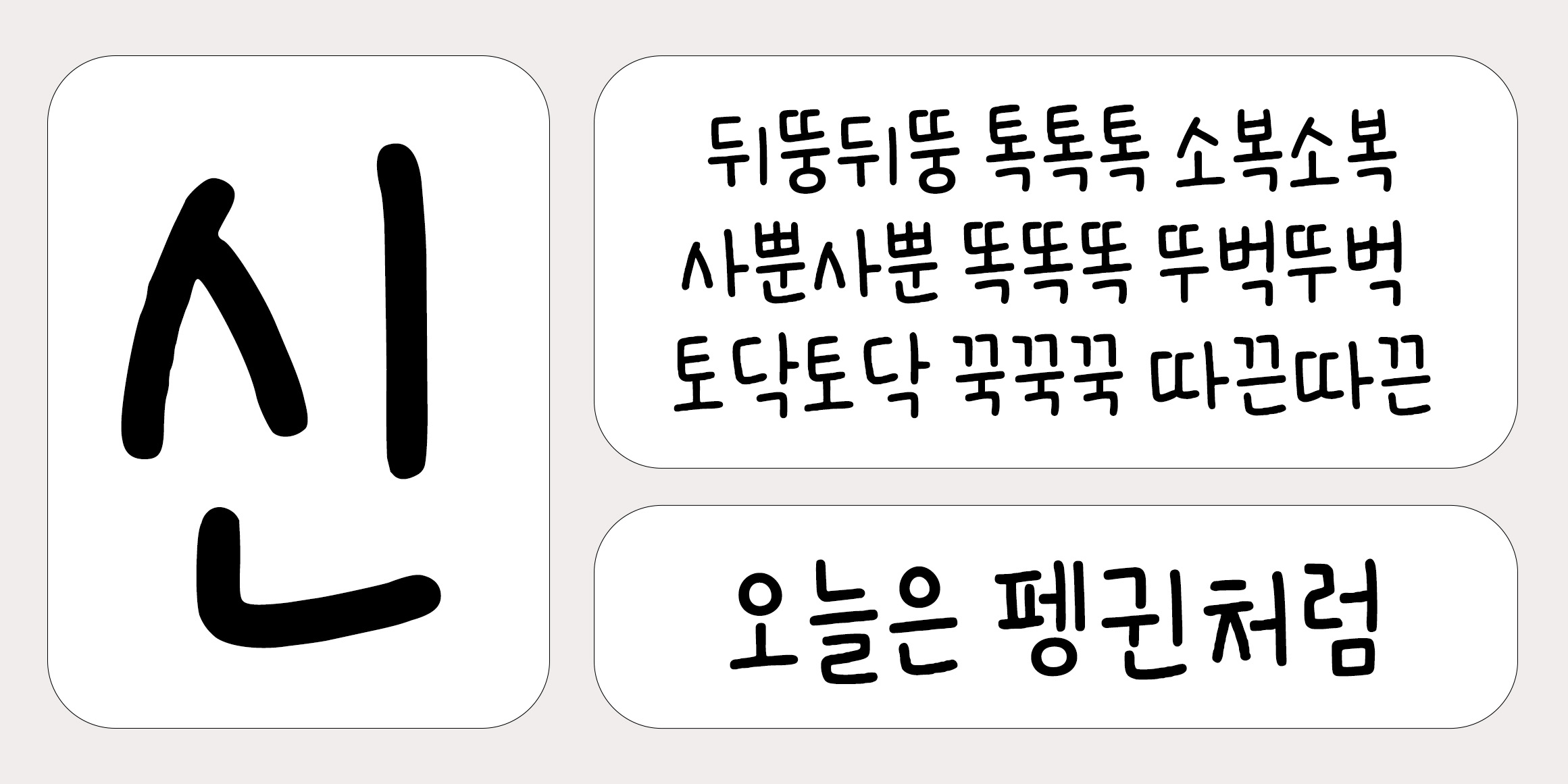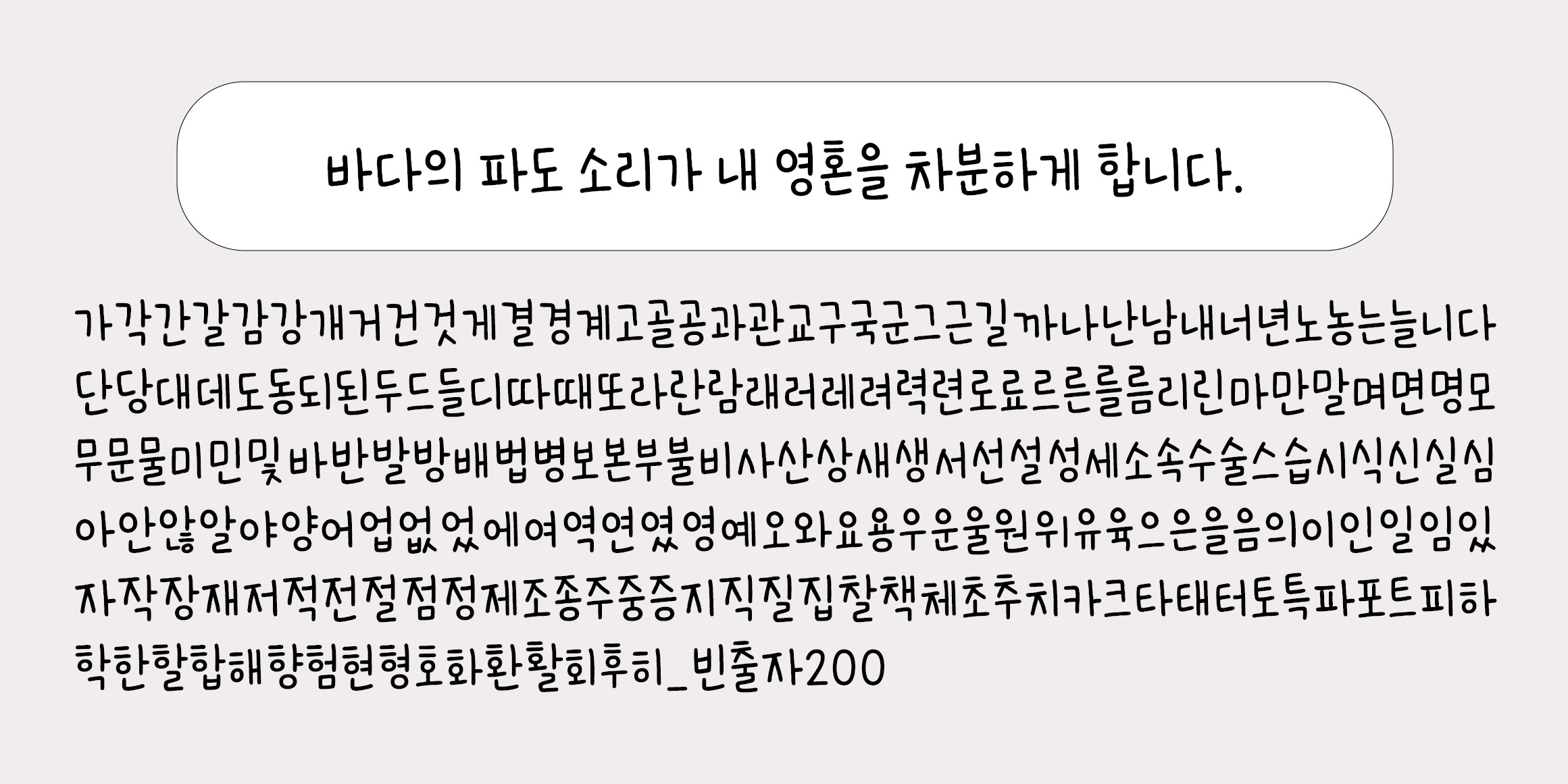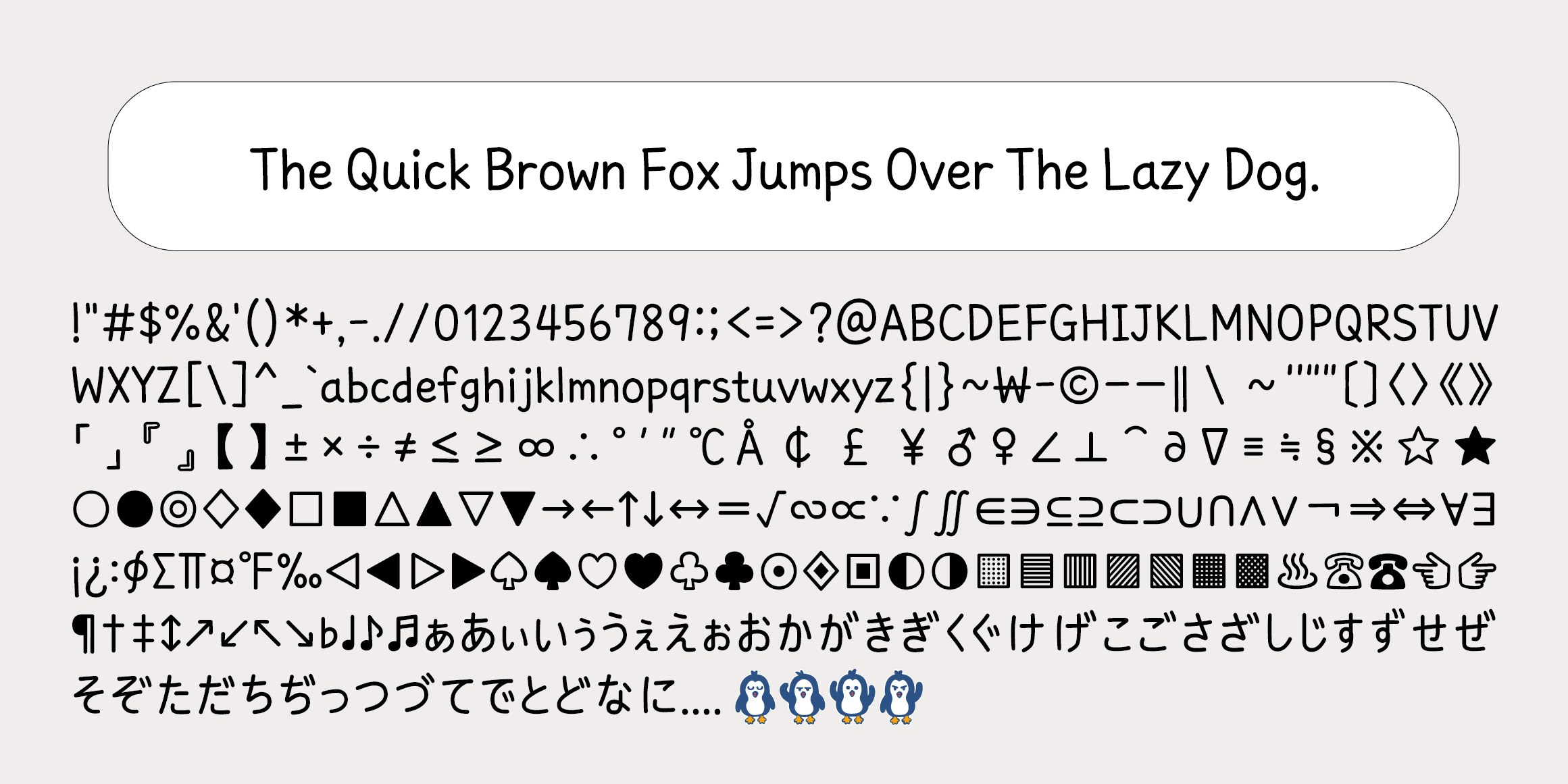
HNT 아무튼펭귄
HappyNewType
분류 Script,손글씨
손으로 직접 쓴 듯한 리듬감이 살아있는 장체 비율에 둥글고 부드러운 획 마감과 기울어진 각도가 어우러져 뒤뚱거리는 듯한 생동감 있는 손글씨입니다.
• 한글 11,172자 / 라틴 94자 / 딩뱃 4자
• HNT 아무튼펭귄 / HNT AnywayPenguin